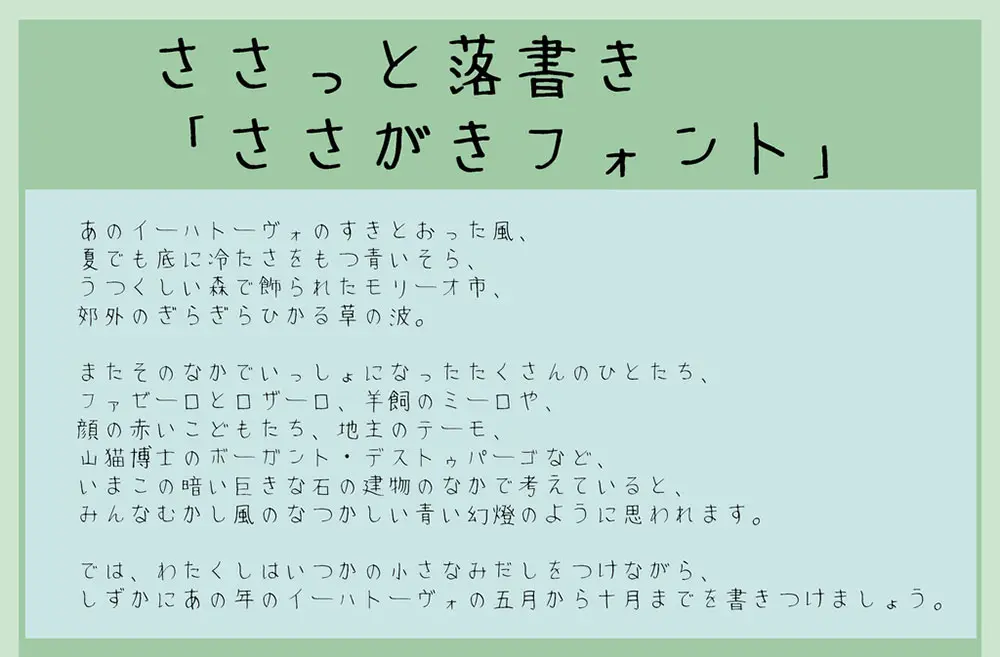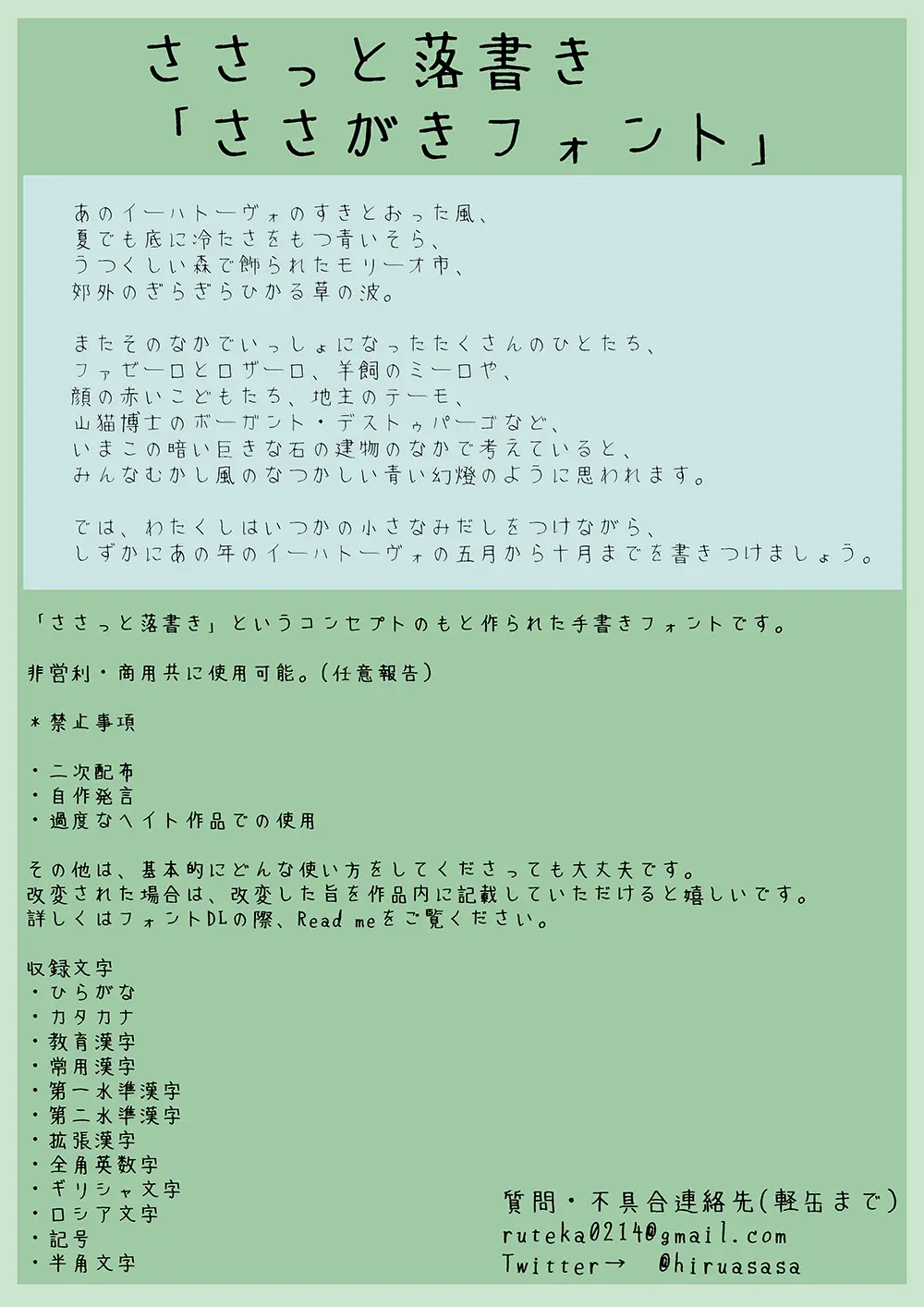
ささがきフォント是一種將作者的手寫文字直接放入的手寫自由字體。
收錄文字:平假名、片假名、教育漢字、常用漢字、第一水準漢字、第二水準漢字、擴張漢字、全角英數字、希臘字母、俄文字母、記號、半角文字。
作者の手書き文字をそのまま落とし込んだ、手書きフリーフォントです。true type形式です。
収録文字、ひらがな、カタカナ、教育漢字、常用漢字、第一水準漢字、第二水準漢字、拡張漢字、全角英數字、ギリシャ文字、ロシア文字、記號、半角文字